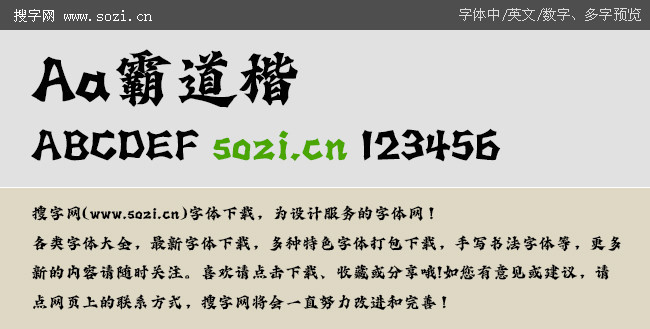
Aa霸道楷
搜字網(wǎng)給大家提供一款A(yù)a霸道楷(非商業(yè)使用)中文字體下載,該字體是一款手寫風(fēng)格中文字體,字形瀟灑大方,霸道十足,非常漂亮,適合包裝設(shè)計(jì)、書裝設(shè)計(jì)、海報(bào)設(shè)計(jì)等應(yīng)用(此字體為個(gè)人非商用版,商用可以聯(lián)系QQ:1006760504)。